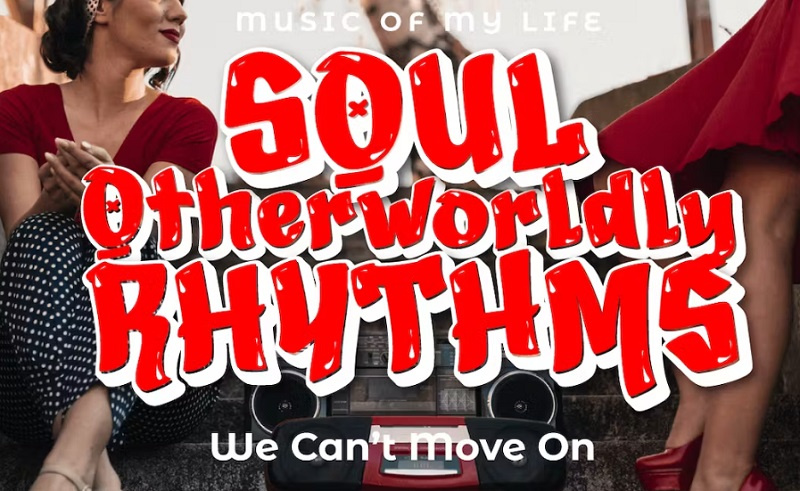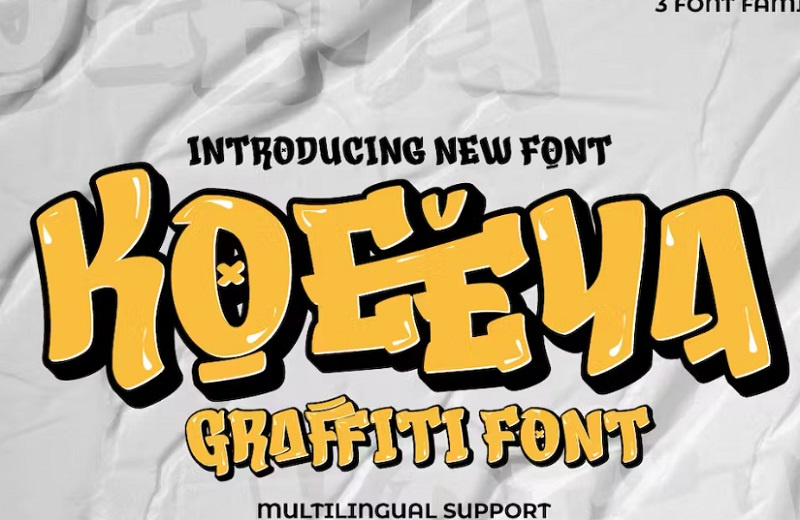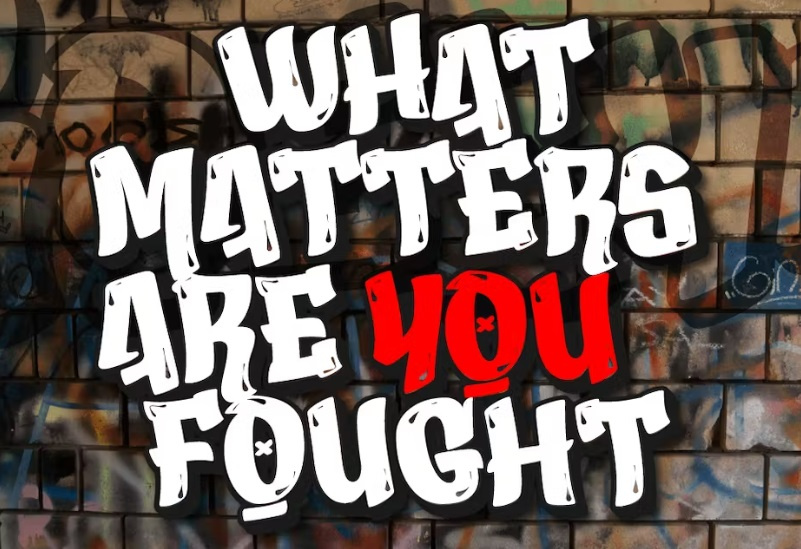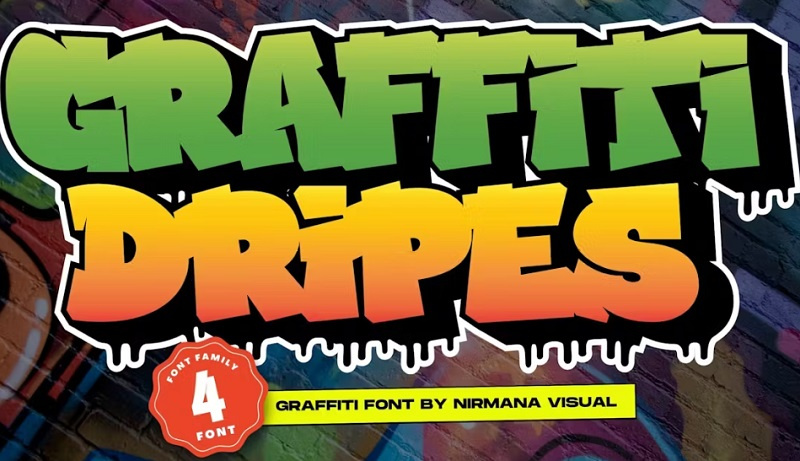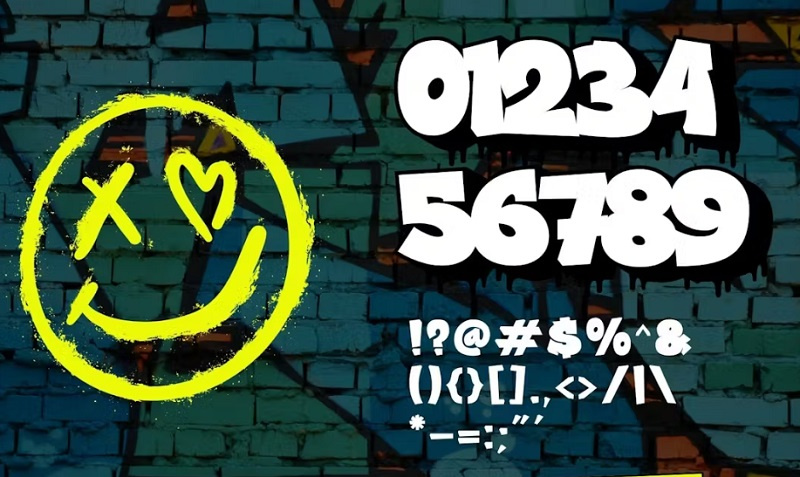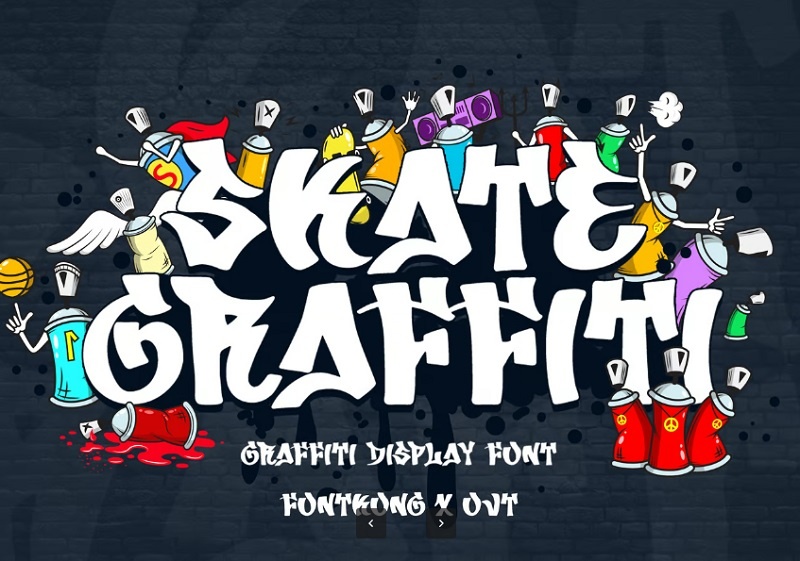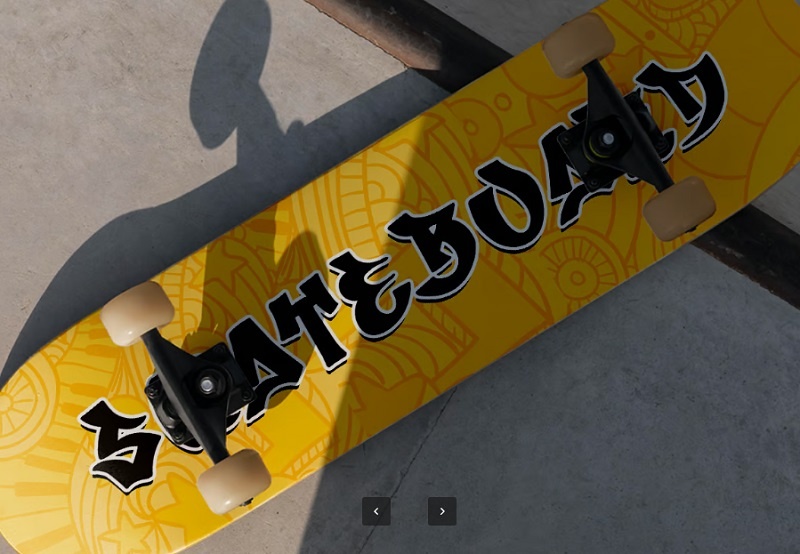
فونت انگلیسی گرافیتی Fast Blaze از جی اف ایکس دانلود. شامل 7 فونت گرافیتی انگلیسی به سبک شهری است که با لبه های تیز و ظاهری پررنگ ارائه می شود. ایده آل برای پوسترهای موسیقی و رویدادهای ورزشی و .... این فونت انگلیسی گرافیتی حس خاصی را به پروژه های شما می بخشد. در ادامه با مشاهده پیش نمایش این فونت ها با ما همراه باشید.
دانلود فونت انگلیسی گرافیتی به سبک شهری Fast Blaze
این فونت گرفیتی انگلیسی با فایل های OTF - TTF و WOFF ارائه شده است. این فونت برای نیازهای پروژه طراحی شما مناسب است، مانند؛ پستهای رسانههای اجتماعی، نقل قولهای شما، کاور های روی تصاویر، آرمهای برچسب، پوسترها، نیازهای چاپی، بنرهای وبسایت و موارد دیگر.
2- دانلود فونت انگلیسی گرافیتی KOEEYA
با استفاده از فونت انگلیسی گرافیتی KOEEYA میتوانید به طراحی تبلیغاتی، پوسترها، طرحهای کالا و موارد دیگر ببخشید و جلوهای منحصر به فرد و شیک ببخشید. اگر به دنبال جدیدترین فونت های انگلیسی گرافیتی هستید حتما این مطلب را دنبال کنید.
3- فونت انگلیسی گرافیتی و نقاشی روی دیوار
این فونت انگلیسی با الهام از طراحی سبک گرافیتی و نقاشی روی دیوار می باشد. فونت Graffiti Dripes تایپوگرافی های زیبایی را برای انواع پروژه های طراحی، از جمله لوگو و برندسازی، پست های رسانه های اجتماعی، تبلیغات و طرح های محصول ارائه می دهد.
4- فونت گرافیتی انگلیسی جدید Skate Graffiti
این فونت گرافیتی، هنر خیابانی را به تصویر میکشد. فایل های فونت با فرمت های TTF، OTF و WOFF ارائه شده است. این فونت انگلیسی گرافیتی برای پوسترها، پوشاک، برندسازی، جلد آلبوم و پروژههایی با سبک شهری ایدهآل است.